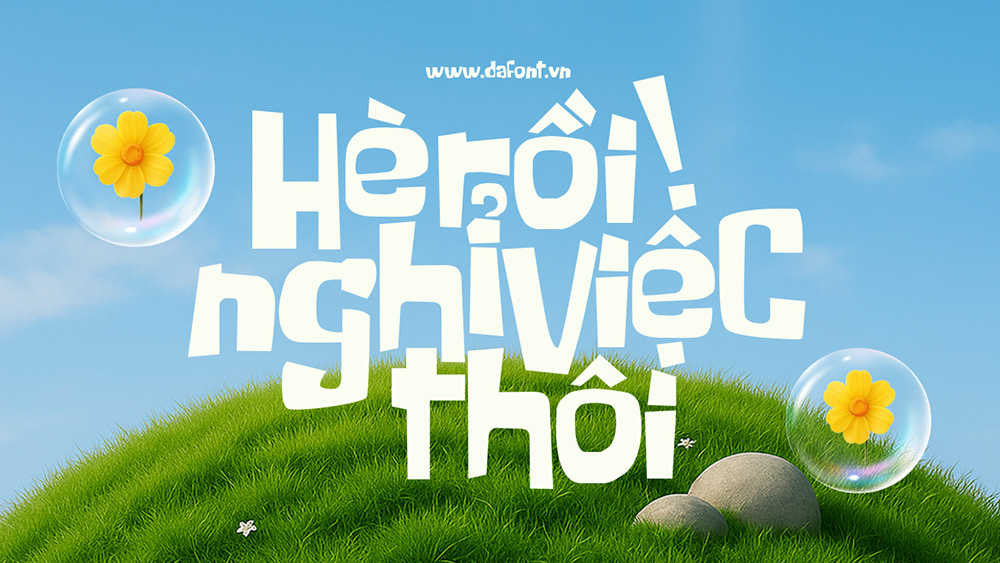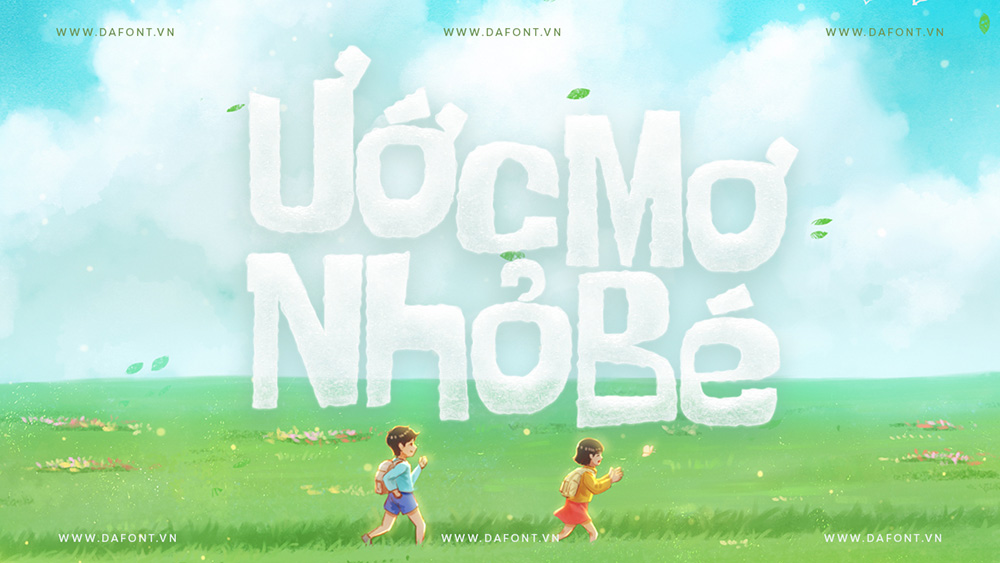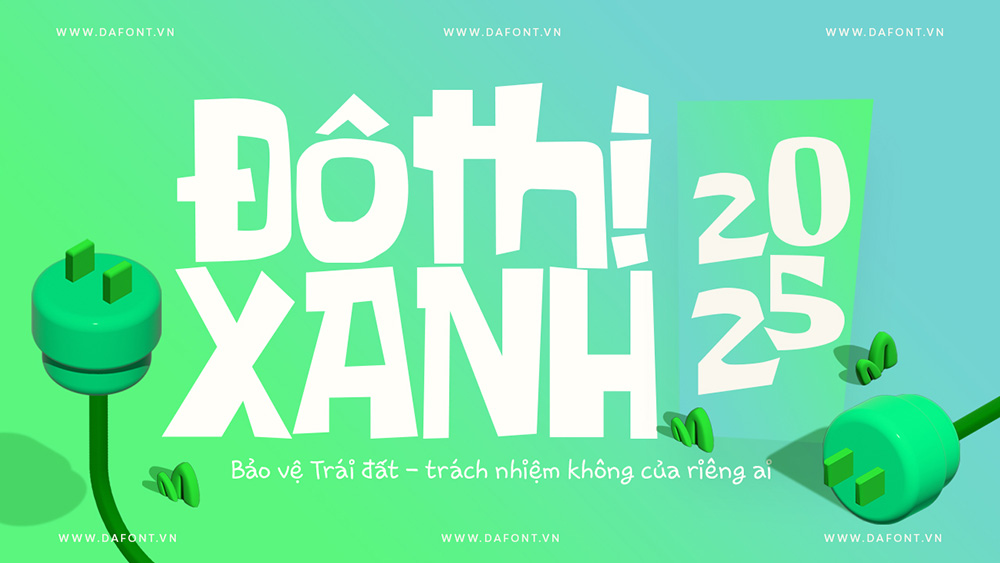
Font Việt Hóa - Some Time Later Mang Phong Cách Vui Nhộn, Ngộ Nghĩnh
Nếu bạn là fan của SpongeBob SquarePants, chắc hẳn bạn sẽ nhận ra ngay phong cách chữ độc đáo xuất hiện trong các thẻ thời gian như “Two Hours Later” hay “One Eternity Later”. Font Some Time Later chính là sự tái hiện hoàn hảo của phong cách đó – vui nhộn, ngộ nghĩnh và đậm chất hoạt hình.
Được thiết kế bởi Fredrick Brennan, font này lấy cảm hứng trực tiếp từ loạt hoạt hình nổi tiếng của Nickelodeon. Những đường nét bất đối xứng, góc cạnh và rời rạc của chữ mang lại cảm giác thủ công, gợi nhớ đến nét đặc trưng của truyền hình cổ điển.
Some Time Later này mang đậm chất thủ công với các nét vẽ không đều, tạo cảm giác như được viết tay. Các ký tự có thiết kế ngộ nghĩnh, góc cạnh và bất đối xứng, gợi nhớ đến phong cách hoạt hình cổ điển, đặc biệt là trong các thẻ thời gian của SpongeBob SquarePants.
- Phong cách: Góc cạnh, bất đối xứng, đậm chất thủ công như viết tay trên giấy.
- Phân loại: Display font – chỉ nên dùng cho tiêu đề, không phù hợp với nội dung dài.
- Sử dụng lý tưởng: Poster vui nhộn, ảnh chế (meme), video hoạt hình, tiêu đề blog, tiêu đề YouTube, Tiktok và các thiết kế mang tính hài hước hoặc sáng tạo.